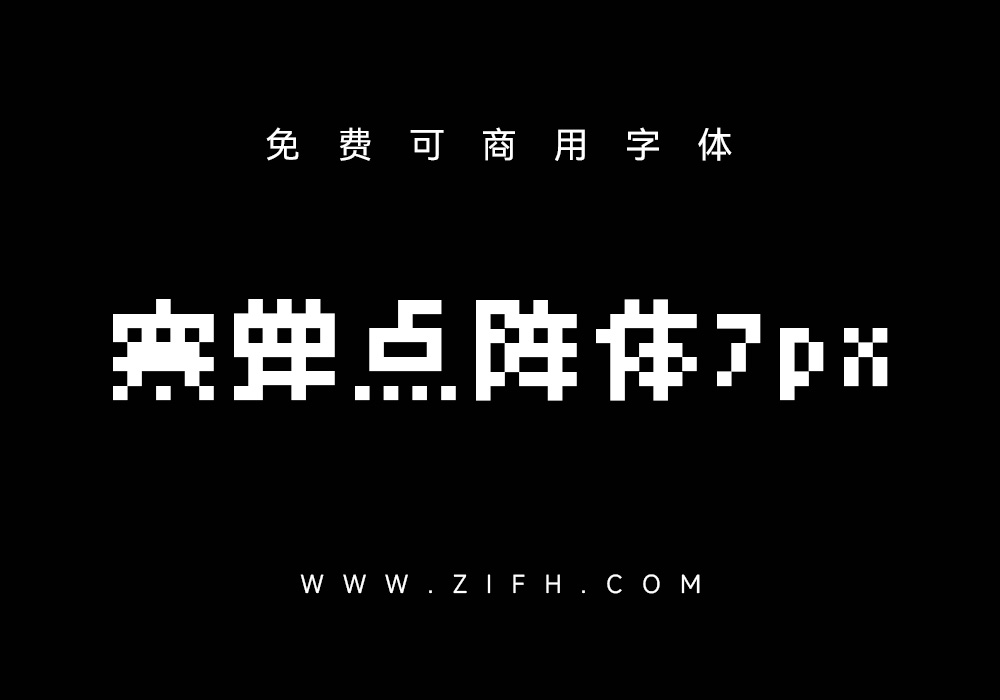
寒蝉点阵体7px:可商用像素风格的中文字体
寒蝉点阵体是寒蝉字型又一套像素风格的中文字库,基于「美咲フォント」修改的字型,融合部分「精品點陣體7×7」字形和极少一部分「Guanzhi 8px」的字形,重新修改设计了英文部分字形和标点符号使其更加协调统一,筛选GB2312字符集调整了近2000文字使字形更清晰耐看,再设计增加1500多字符,是集日文、繁体、简体、英文共13600个字符的大成之作,使用更方便。